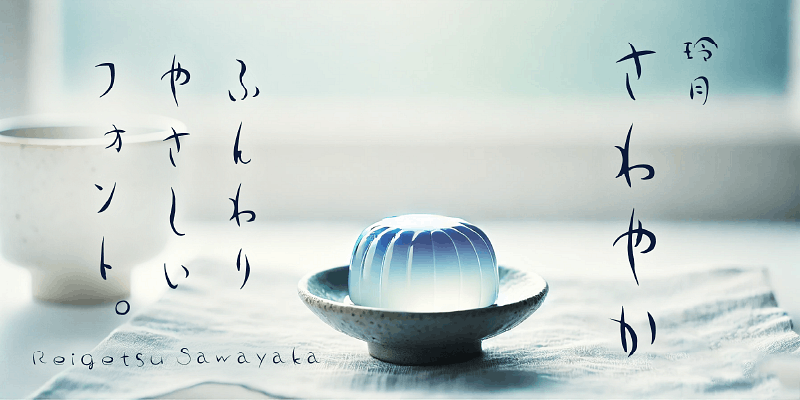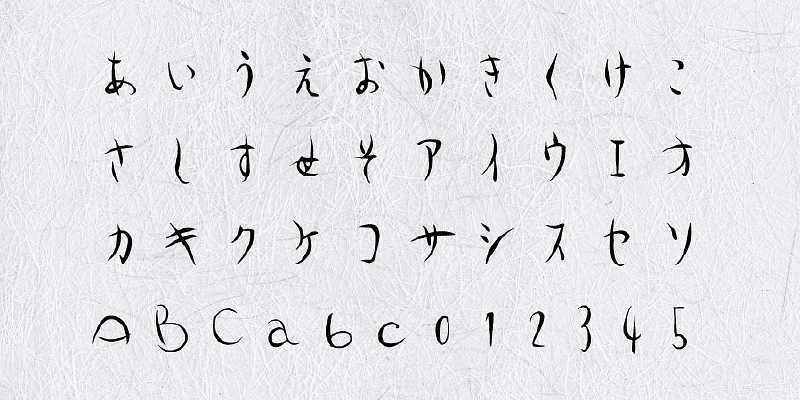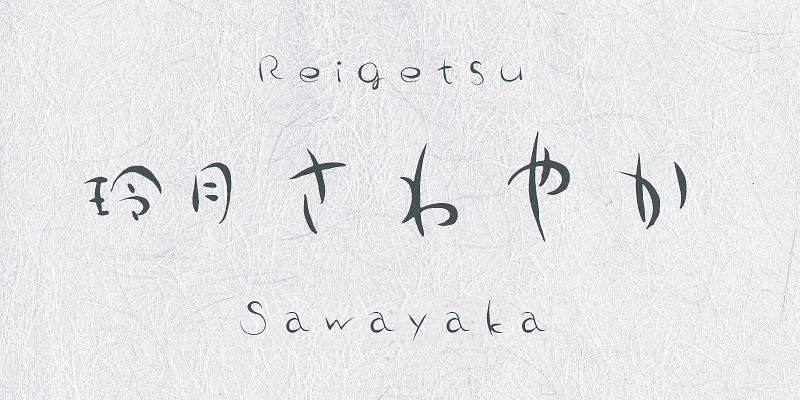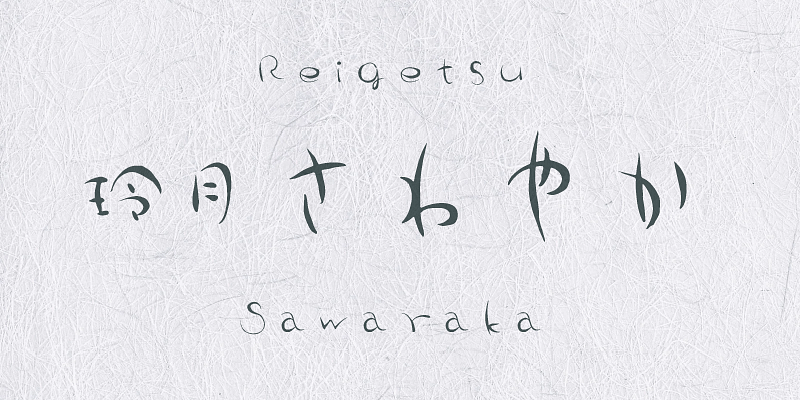
Diese Schrift behält die grundlegenden Eigenschaften von AB-Reigetsu_yawaraka bei, ist jedoch so gestaltet, dass sie in noch stärkerem Maß ein „erfrischendes“ Gefühl vermittelt.
Diese Schriftenserie enthält handgeschriebene japanische Originalschriften, die auf Kalligrafie basieren und 2002 veröffentlicht wurden. Mit ihrem warmherzigen Aussehen lenken diese Schriften das Auge des Lesers auf die wichtigsten Punkte eines Designs.